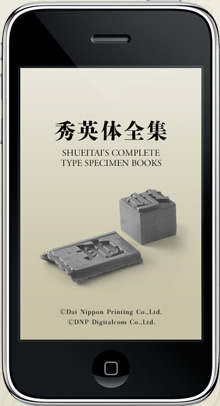
「秀英体全集」をAppStoreで発売開始
明治から昭和にかけてDNPおよび秀英舎が発行した活字見本帖全32冊を、毎週新刊を追加しながら配信します。配信する見本帖は、日本の書体デザイン史における非常に貴重な資料であり、デザイナーや印刷分野の研究者などにおすすめです。
初回配信ラインナップ
壱号明朝活字見本帳(大正15年8月5日発行)/34ページ
壱号ゴヂック活字見本帳(大正15年9月5日発行)/26ページ
活版見本帖 Type Specimens 和文編(大正2年8月発行)/26ページ【無料】
活版見本帖 Type Specimens 花形・地紋編(大正2年8月発行)/63ページ
活版見本帖 Type Specimens 書形編(大正2年8月発行)/45ページ
活版見本帖 Type Specimens 欧文編(大正2年8月発行)/59ページ